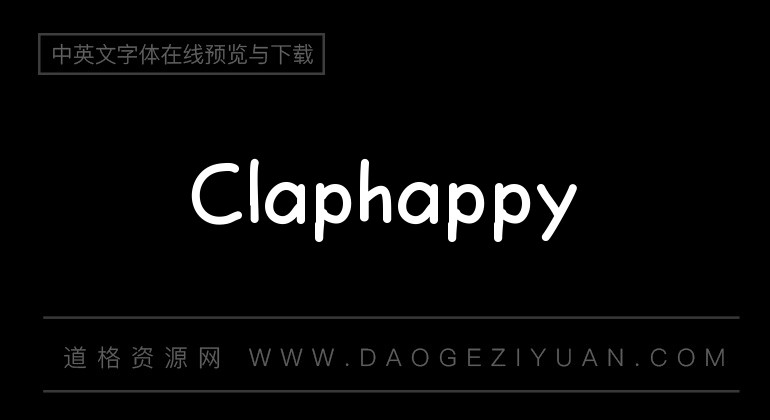
Claphappy 字体是一种简洁、活泼、时尚的手写字体,具有鲜明的视觉特色,可以带来温暖的感觉。它以更自然的笔画和更舒服的节奏,让你的文字更有趣。它可以用于各种商务、广告、宣传物料等,为你的设计增添活泼的气息。内容介绍
Claphappy是一款非常不错的手写艺术字体,具有很好的视觉感,适合于文化类的宣传设计、商业类品牌的广告和产品包装设计以及个性化文字排版等较多场景。